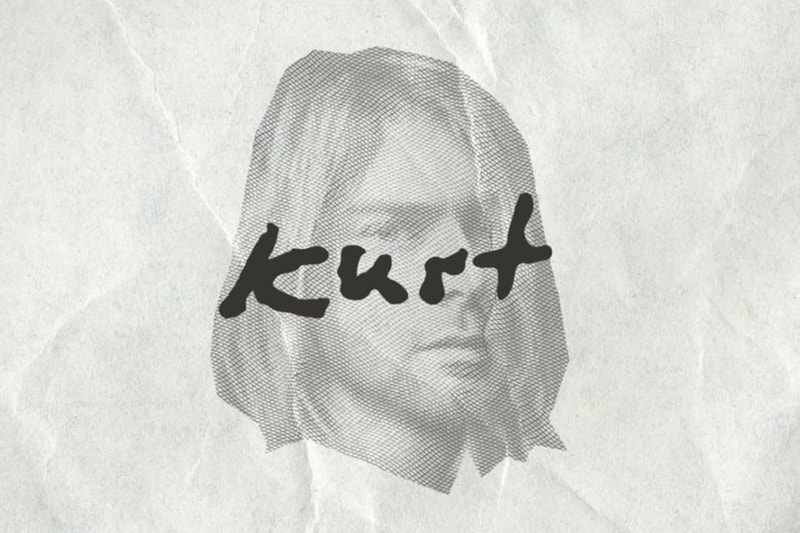
UPDATE:フランス人デザイナーが世界を熱狂させたシンガーソングライターらの直筆フォントを開発
カート・コバーンやジョン・レノン、デヴィッド・ボウイなど錚々たる面々の手書き文字がラインアップ(UPDATE:知的財産権の問題でWebサイトが閉鎖、フォントの配信も中止に)
今やスターの直筆サインや手紙はオークションで数億円という破格の値段で落札合戦が繰り広げられるほど、コレクターにとっては見過ごせぬアイテムとなっている。我ら『HYPEBEAST』でも世界の様々なアート作品やスニーカーといったレアものをご紹介してきたが、今回は世界を熱狂させたロックミュージシャンたちが残した手書き文字のフォントをお届け。
フランス人デザイナーのNicolas Damiens(ニコラス・デイミアン)とJulien Sens(ジュリアン・センズ)が立ち上げたこの“Songwriters Fonts”では、伝説的ロックバンドNirvana(ニルバーナ)のフロントマンとして人気を博し、27歳という若さでこの世を去ったKurt Cobain(カート・コバーン)やオノ・ヨーコの夫でありThe Beatles(ザ・ビートルズ)のボーカル/ギタリストとして活躍したJohn Lennon(ジョン・レノン)、2016年に癌で死去した英国が誇るカリスマアーティストDavid Bowie(デヴィッド・ボウイ)など、様々なロックスターたちの手書き文字をサンプリングし、Web用のフォントとして無料配信している。
「Songwriters Fontsとは、インスピレーションに関するものです。影響力のあるソングライターの手書き文字で歌詞を書くことは想像力が膨らむのを手助けしてくれることでしょう。David BowieやCurt Cobain、John Lennon、Serge Gainsbourg(セルジュ・ゲンスブール)、Leonard Cohen(レナード・コーエン)の雰囲気に浸ることは、想像力に富んだ体験になるかもしれません。それがまさにポイントなのです」